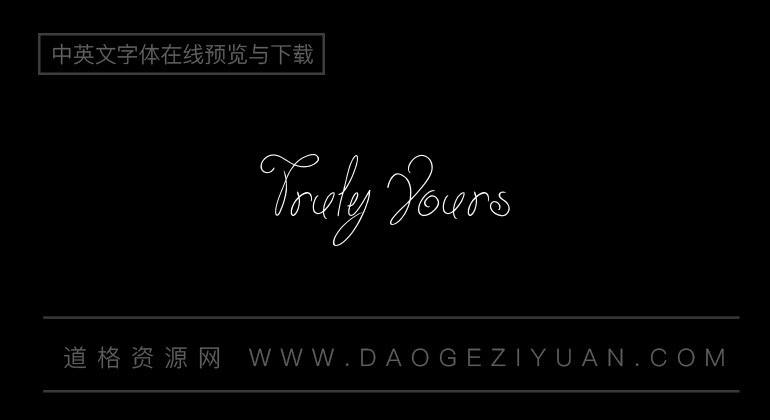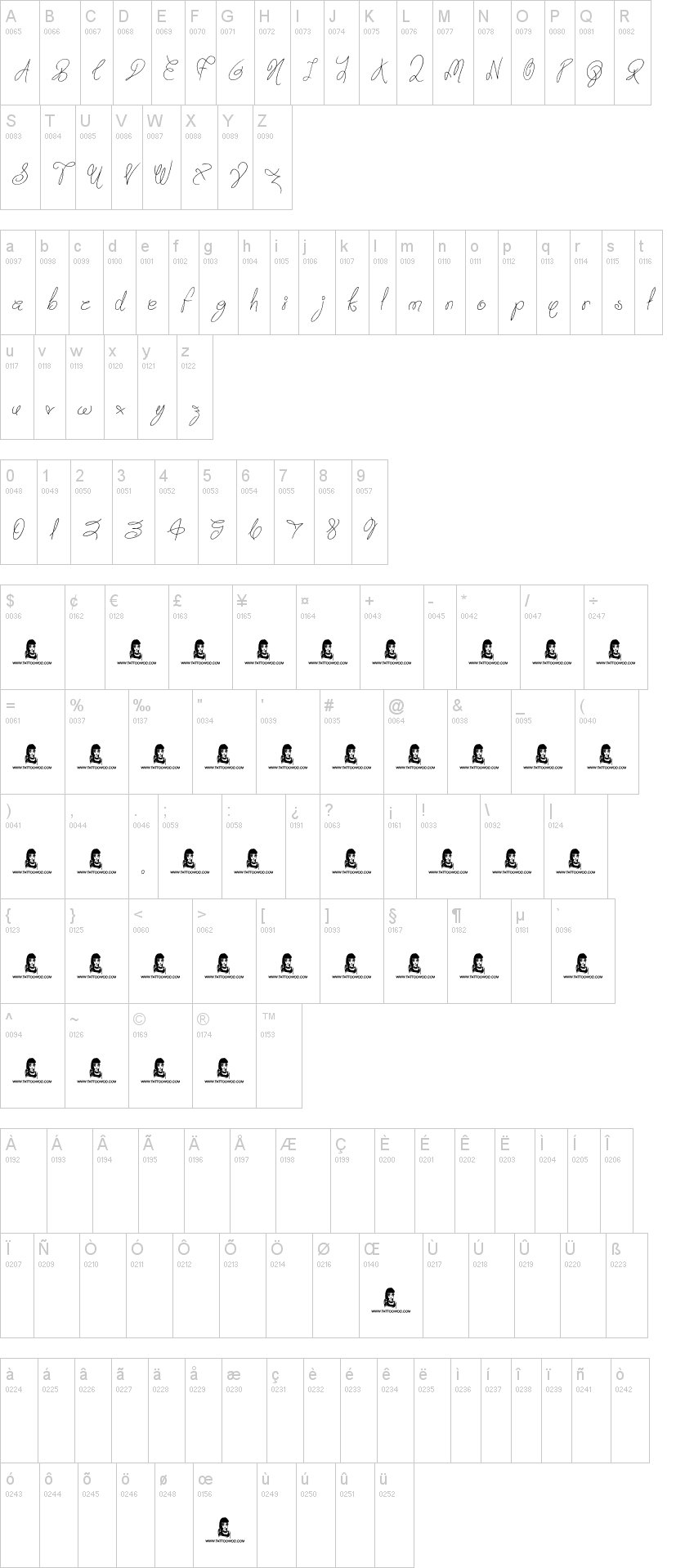
? Truly Yours字体是一种细腻优雅的美式手写字体,它具有流畅的笔画,有助于增加文本的可读性。Truly Yours字体的字形比较舒展,它的细节和折痕使字体显得更加细腻而优雅,更有活力。Truly Yours字体可以用于各种场景,如婚礼邀请函,海报,标志或标语等。内容介绍
Truly Yours是一款非常不错的手写艺术字体,具有很好的视觉感,适合于文化类的宣传设计、商业类品牌的广告和产品包装设计以及个性化文字排版等较多场景。